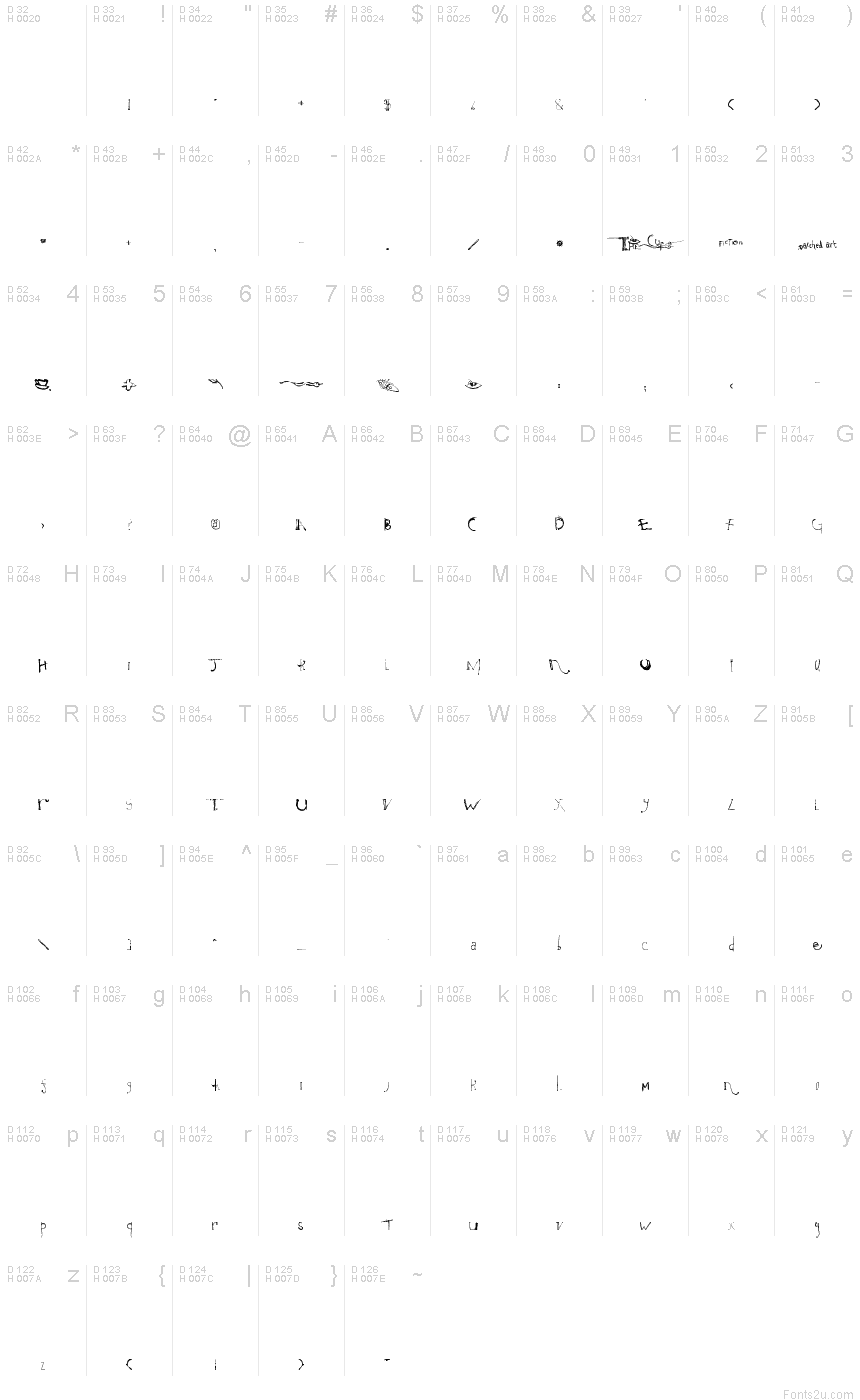
Caterpillar od MintCure to darmowy "trashowy" krój pisma o zadziornej, ręcznie rysowanej energii, przypominającej tusz naniesiony na szorstki papier. Nieregularne krzywe, poszarpane krawędzie i lekko chwiejny rytm nadają mu niespokojną osobowość, która natychmiast przykuwa wzrok, nie tracąc przy tym na czytelności.
Dzięki Caterpillar nadasz dziki, organiczny klimat tytułom zinów, plakatom horrorów, okładkom albumów grunge, odważnemu brandingowi, etykietom produktów handmade i eksperymentalnym grafikom do mediów społecznościowych. Ten darmowy font świetnie sprawdza się w dużych rozmiarach, gdzie jego chaotyczne detale pozostają wyraźne. Aby zachować równowagę i czytelność w mniejszych tekstach, warto zestawić go z czystym krojem bezszeryfowym.